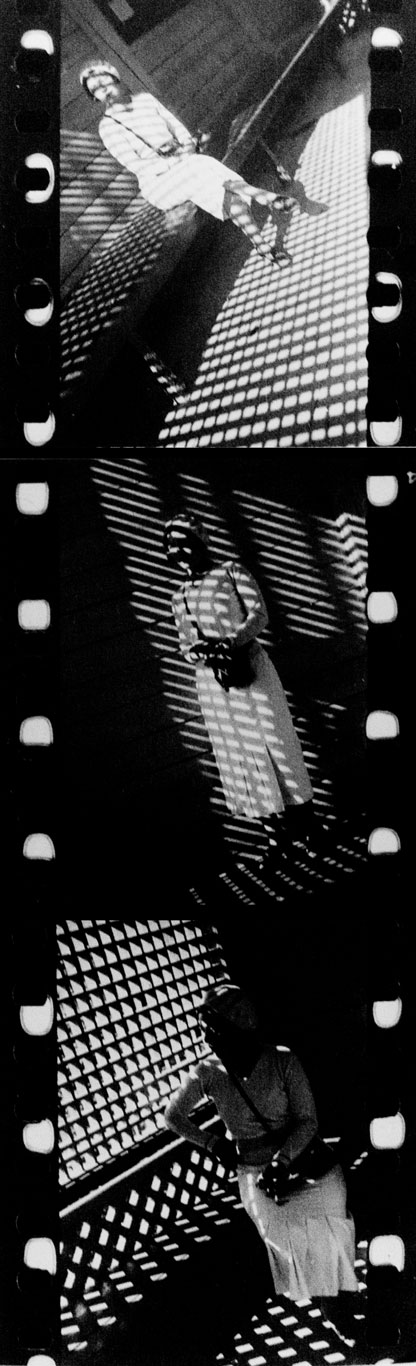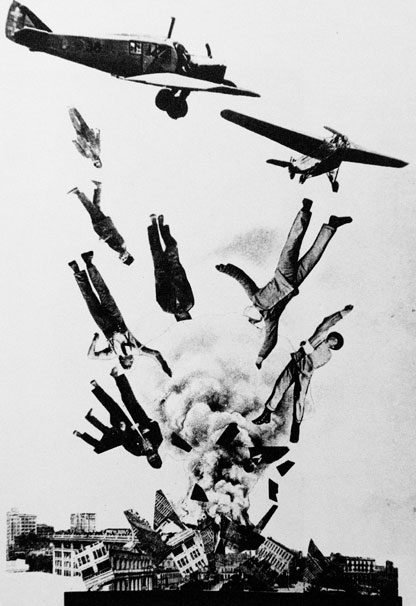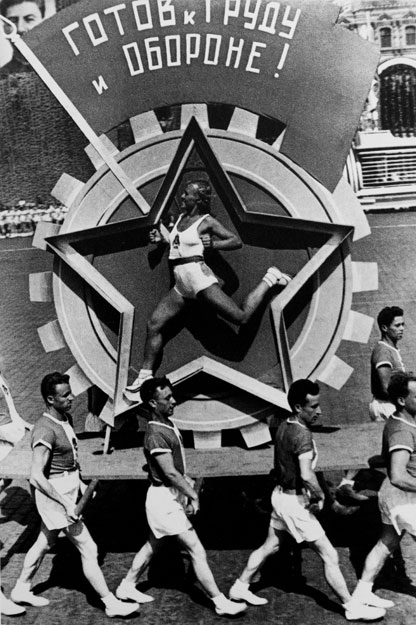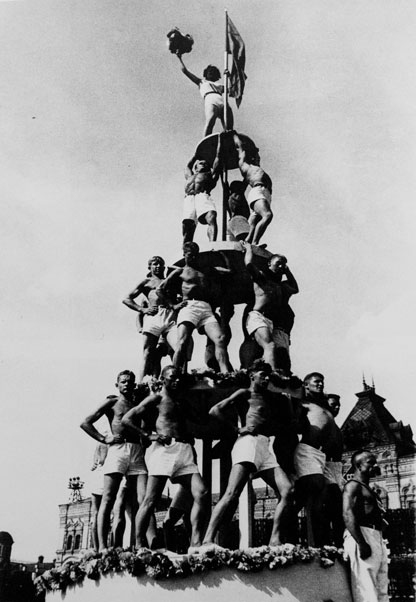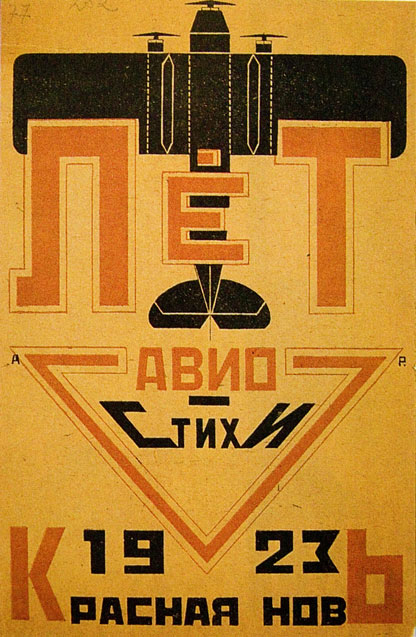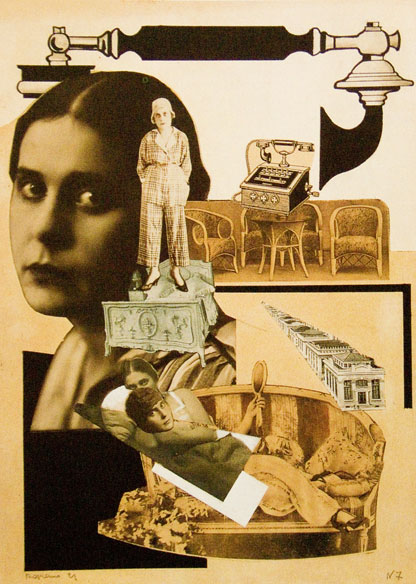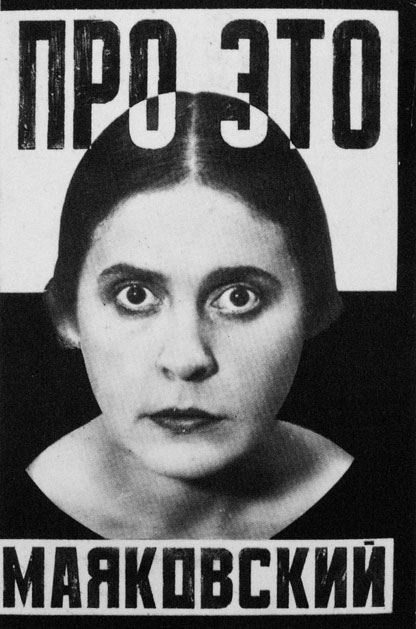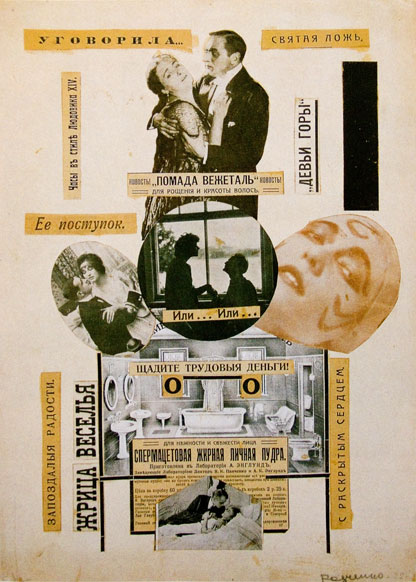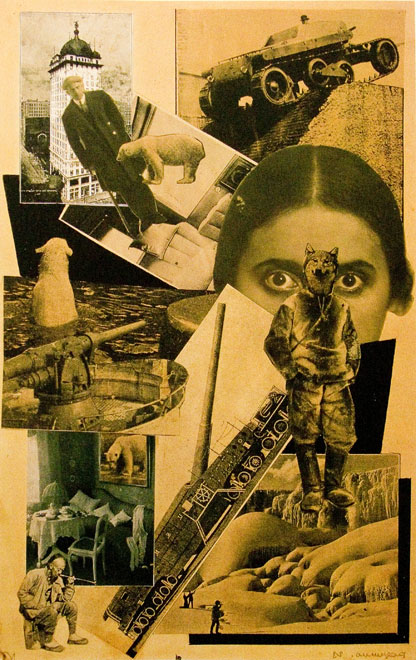
L’exposition Rodchenko qui se tient au MaM (Musée d’Art Moderne de la Ville de Paris se termine bientôt, il n’est que temps de le rappeler et de vous pousser à y faire un saut sans la moindre hésitation.
Rodchenko fut l’un des plus grands graphic-designers de tous les temps. Il défricha le terrain des espaces graphiques, inventa le photomontage moderne et fit œuvre photographique des plus pregnantes. Témoin privilégié d’une époque et d’une société russe en voie de recomposition après la révolution d’oktober 1917, il fut récupéré comme nombre d’artistes par le régime pour servir de levier de propagande à celui-ci. Il fut peu peu sollicité pour des travaux dont l’unique objet était de sublimer l’homme nouveau, la renaissance sociale tournée vers un monde meilleur. On est encore loin d’avoir découvert les charniers de Staline et le Goulag. Mais de fait, la Russie de tous les empereurs avait vécu. La société russe améciée se nourissait exclusivement d’espoir d’un monde idéalisée d’où pauvreté et misère seraient chassées. Les artistes étaient ainsi conviés à participer à la construction de l’homme nouveau, le pionnier, restructuré, pour ne pas dire reformaté.
Que ce soit dans la vie de tous les jours, dans l’activité industrielle ou tout simplement sportive, l’artiste se devait de créer une vision de la société débarassée des styles ampoulées de la fin du XIXe siècle pour et à la gloire de la nouvelle modernité. L’Histoire était en marche, l’Histoire dont Hegel et Marx avaient annoncé la fin avec l’avènement du communisme. L’époque se prêtait donc aisément à cette reconsidération révolutionnaire de l’espace graphique qui fit des émules jusques sur la cinqième avenue à New York après la deuxième guerre mondiale, Alexey Brodowitch en fut l’un des plus âpres promoteur. Le style constructiviste russe ne fut jamais abandonné ni oubliée. Il participe depuis 90 ans à notre espace de communication de tous les jours. Sans doute que le communisme a disparu, mais pas la vision moderne que celui-ci donna à voir de l’homme et de la société. Neville Brody dans les années 80 sut retrouver avec efficacité et un immense talent ce style pour mettre en scène pochettes de disques et magazines (The Face etc.).
portrait du grand poète Vladimir Mayakovsky, 1924
Vladimir Mayakovsky, 1924
Marie Chvetsova dans un jeu de miroirs, 1924
Varvara Stepanova, 1924
Mother, 1924
portrait à double exposition du peintre Alexandre Chevtchenko, 1924
Varvara Stepanova (l’épouse et collaboratrice de Rodchenko) avec un foulard, photographie peinte à la main, 1925
triple portrait, Julia Solntseva et de son mari Alexandre Dovjenko et du poète futuriste, Alexeï Krouchenikh, 1930
Regina Lemberg, 1934, élève en photographie de Rodchenko
fille au Leica, variantes, 1934
nature morte avec Leica, 1930
série d’illustrations photographiques pour le livre d’enfants de Serguei Trétiakov
Les travaux de Rodchenko qui transforment peu à peu son œuvre potographique en œuvre graphique.
Dire q’il s’agit d’une rupture. Non, d’abord peintre plasticien, décorateur, Rodchenko est venu à la photographie assez tard, et son attrait pour les portraits humanistes témoigne de son amour du prochain. Mais le graphiste, l’affichiste reprend la main pour structurer ses espaces photographiques, cherchant à utiliser lignes de fuite, structures urbaines et surtout installant pour la première fois dans l’histoire de la photographie la perspective diagonale, sans doute au départ comme jeu d’agrandissement de son champ de vision trop enfermé dans le format 24×36 de son Leica. Peu peu ces diagonales lui donneront l’idée, conjointe avec le DaDa qu’il découvrit vers 1915-1920, de structurer ses affiches et couvertures de magazines avec ces mêmes lignes de fuite et parallèles diagonales. L’esprit constructiviste russe était né.
une cruche, 1928
Couverture, 1923, jeu de montage entre avion et lettres capitales pour donner l’impression d’un survol de paysage
photomontage pour le livre Pro èto de Vladimir Maïakovski, 1923
photomontage parodiant les mélorames traditionnels, publié dans le magazine Kinophot, 1922
photomontage pour le livre Pro èto de Vladimir Maïakovski, 1923
couverture magazine LEF, n°3, 1923
Affiche publicitaire pour une série de journaux filmés de Dziga Vertov, 1924
Couverture de livre pour Mess-Mend, 1924
photomontage pour le magazine Au Loin. L’Europe avant la Seconde Guerre Mondiale… caricature des citoyens qui applaudissent ou sifflent les politiques à chaque faux pas de leurs dirigeants, 1930